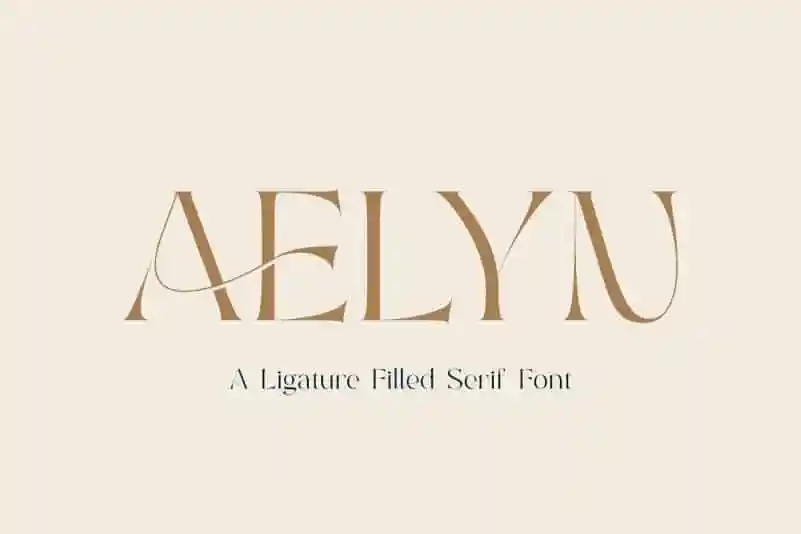
Aelyn Serif Font
Aelyn Serif Font é uma fonte elegante e feminina, desenvolvida por Surplus Type Co., disponível na categoria de serif fonts através do site 99designs. Conhecida pela sua versatilidade e estilo único, Aelyn oferece alternativas estilizadas, ligaturas estilizadas e suporte para várias línguas, tornando-a ideal para designers que desejam adicionar personalidade e sofisticação a seus projetos. Com um amplo conjunto de ligações tanto em letras maiúsculas quanto minúsculas, Aelyn é perfeitamente adequada para aplicar em marcas de luxo, designs de sites elegantes e materiais de estaçãoaria premium. Esta fonte traz não apenas beleza, mas também uma ampla gama de possibilidades que tornam a Aelyn uma escolha valiosa para diversos projetos gráficos que exigem elegância e sofisticação.